它是一篇由海外室内设计师写的字体样式新手攻略,非常狠下功夫,从字体样式的归类(包含历史时间和网页页面规范等),字体结构独特到创意字体设计方案等都是有细腻详尽的叙述
为什么要关注
从应用性的视角考虑,近期愈来愈多的网址及其图形创意新项目中规定我需要设计方案一个汉语的版本号。或许你也立刻也会遭遇这种要求。
从学生的视角看来,中国字真的是酷毙了!大家都知道,汉语是现阶段仍在被应用的最历史悠久的撰写管理体系,值得一提的是,全部亚洲地区地域的撰写语系都好像汉语的一个支系。虽然这种语系早已演变成别的独特与众不同的形状,可是你一直在在其中依然能够 见到中文字符的影子。
自然,也有一点必不可少的缘故便是:汉语十分的幽美。谁会回绝赏析美好事物呢?
开头难:简体中文版VS繁体
你清楚吗,在汉语的撰写管理体系有二种规范。
长话短说,在1949年毛泽东推动中国共产党当政后,他发觉能够 根据减少文本的复杂性来提升人民的识字率,因此他机构了许多教育学家修定了开始了文本简单化健身运动。wiki百科(英语版)告知大家:
“中国共产党各自在1959年和1964年公布了初次官方网文本简单化的文档”
在那时候,中国香港、中国台湾及其澳門并不会受到内地层面操纵,因此 她们并沒有更改字型,只是再次保存了原来的繁体。在简化字宣布公布前,世界各国早已有很多的中国移民及其唐人街探案2,因此 在这种地区她们仍然在应用繁体。
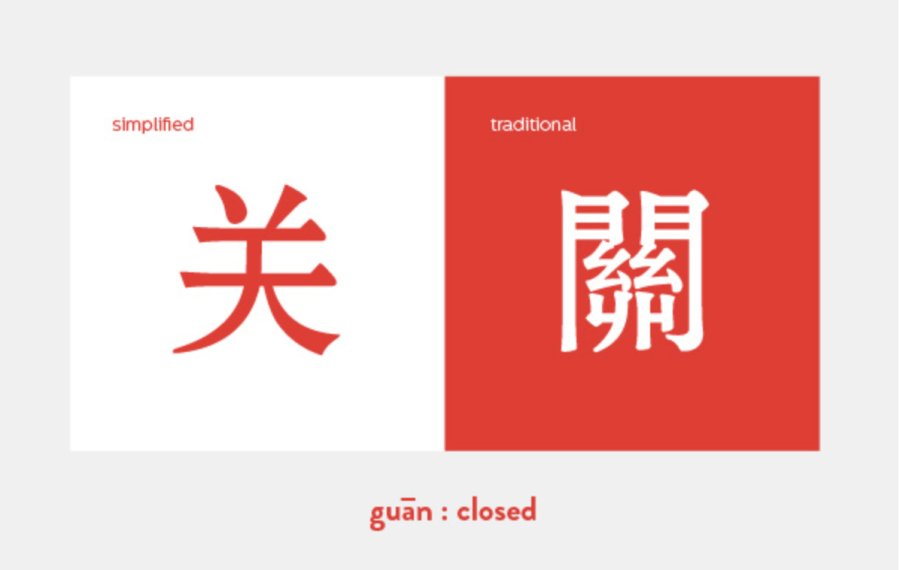
应用简体中文版的地区:
做为中国内地的官方网撰写語言,自打1954宣布公布至今就出現在各部。
应用繁体的地区:
做为中国香港、中国台湾及其澳門的官方网撰写語言我国海外创建的唐人街探案21954年前中国内地的老古董书原文中在中国内地的一些十分官方网的地名大全或是横匾上在汉语简单化前就早已支系的这些语系,例如:日语、韩语及其初期的越南语
啊!简直喝醉!
额滴神啊!如潮汐一样的标识符!
设想一下这种历史时间针对字体样式产品研发个人工作室代表着哪些:以便公布一个技术专业的字体样式,她们不但必须建立一个包括超出20000字符的字符集,她们还必须反复2次工作中,一次是接下来的,一次是繁体字的。并且这都还没充分考虑多种多样文本大小水平!
哪些?我刚才讲过20000?
是否早已吓傻?虽然早已干了简单化,可是技术专业的字体样式务必要包括大概20000种字型,有时候将会会再多几千种,有时候将会会少一些。这在其中还包括了英语的英文字母,汉语及其英语的国际音标英文字母,及其巨大的汉语标点集。繁体的字符集则最少要包括30000种字型。一些外行的字体样式将会会只是包括大概2000种常见的字型,可是这种字体样式不应该被选来作为关键字体样式,由于有的情况下你能发觉它失去了你必须的文本。
怎样在@font-face及其网络字体中应用他们?
回答是不可以应用他们。我国都还没添加@font-face,她们依然坚持不懈应用原来的电脑浏览器规范字体样式及其独特种类应用的PNG/SVG。由于字体样式中包括了过多的字型,每一种字体样式的文档一般有3-7MB,这容积易如反掌额地就击败了网页页面中置入的內容。了解近期才出現了一些非标网页字体3D渲染的极端化试验技术性。